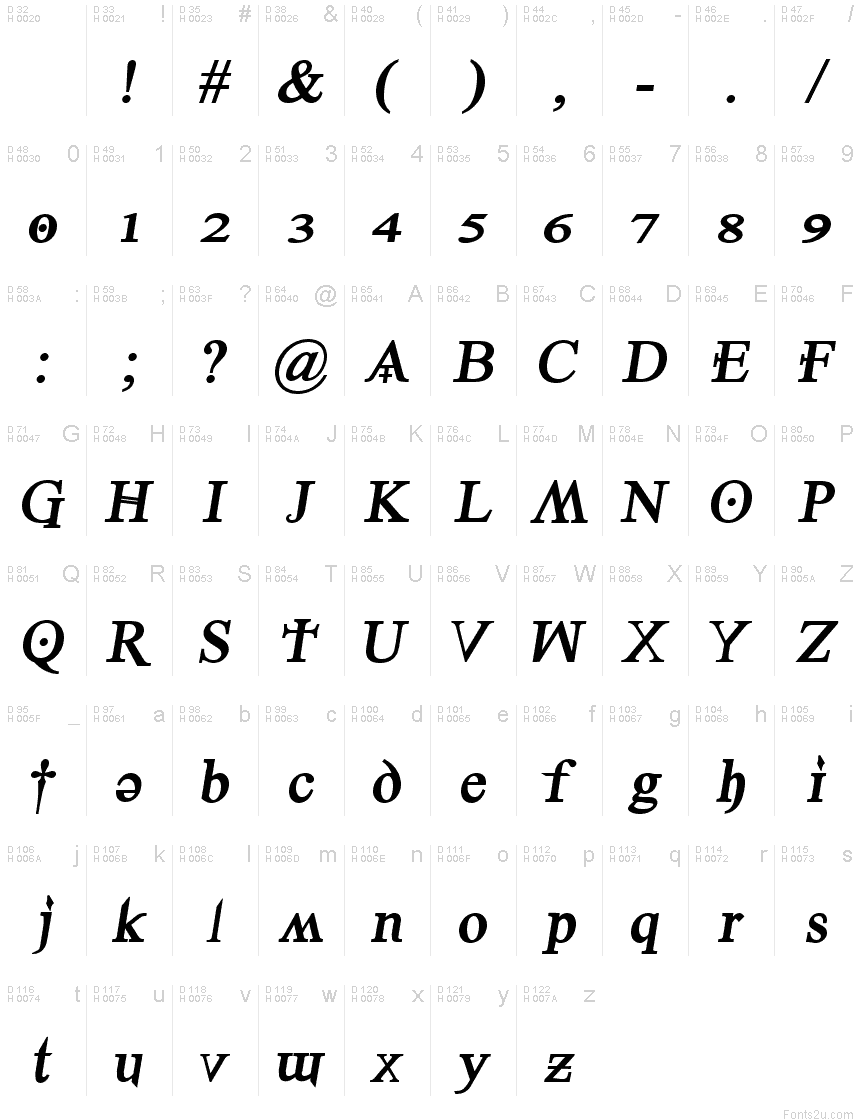
Denial 2 Bold Italics od SD Fonts to darmowy krój szeryfowy o wyrazistej, rzeźbiarskiej energii, która sprawia wrażenie niemal ręcznie wycinanej. Litery pochylają się z pewnością siebie, z grubymi, rozszerzającymi się pociągnięciami i nietypowymi krzywiznami, które nadają każdemu słowu dynamiki. W rodzinie Denial 2 ta odmiana wypada jak głośne, teatralne rodzeństwo – jest wyrazista, mocna i nieco przekorna.
Dzięki Denial 2 Bold Italics nagłówki i tytuły natychmiast zyskują charakter, co czyni ten darmowy font naturalnym wyborem na okładki książek, plakaty, logotypy, wyraziste opakowania i odważne projekty redakcyjne. Świetnie sprawdza się w krótkich, dużych tekstach, gdzie jego krzywizny i kąty mogą w pełni wybrzmieć. W mniejszych rozmiarach warto połączyć go z czystym, neutralnym krojem bezszeryfowym, aby zachować czytelność, pozwalając jednocześnie Denial 2 zadbać o dramaturgię.